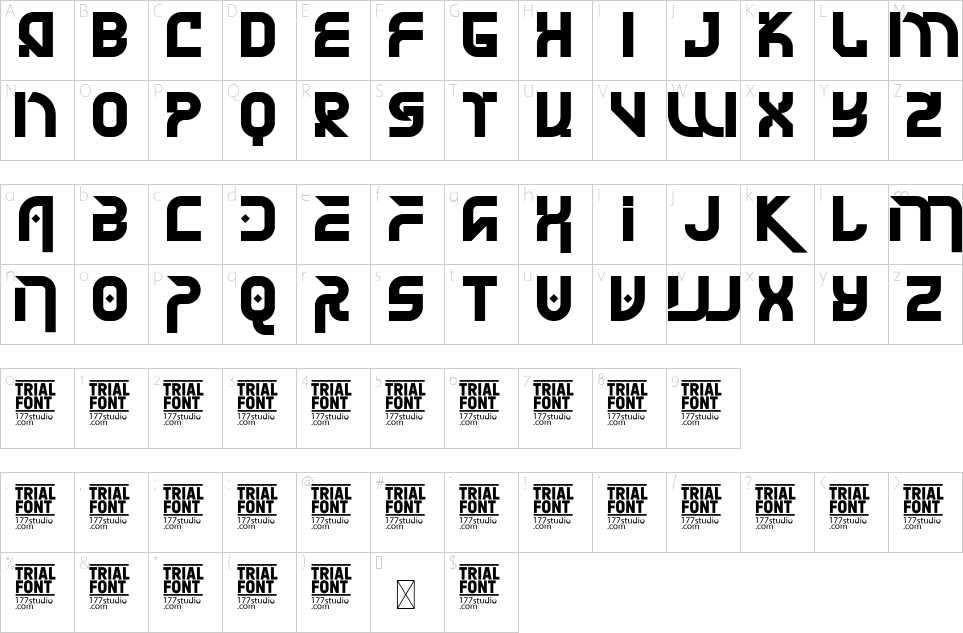
Descubra Process Mastery, uma elegante e profissional fonte gráfica que complementará sua identidade visual. Desenvolvida pelo 177studio.com, Process Mastery foi projetada para ajudar profissionais a organizar e comunicar seus processos de forma clara e eficaz. Esta fonte é uma escolha perfeita para designers, técnicos ou qualquer um que precise de uma fonte que funcione bem tanto em projetos digitais quanto em impressão. Com 1001 fontes gratuitas disponíveis, o catálogo de 177studio.com é um acervo incomparável para qualquer designer. Process Mastery está entre elas, oferecendo uma combinação única de letrasete e legibilidade que é indiscutivelmente útil para manusear processos complexos de forma simplificada. Desenvolvida por uma equipe experiente, esta fonte atende a uma ampla gama de necessidades, tornando-a um investimento valioso para qualquer projeto de design. O design clean e minimalista de Process Mastery torna-o uma opção versátil para diversos ambientes, desde ambientes de trabalho profissional até design de interfaces de usuário intuitivas. Seja para um documento técnico, um mural de projetos ou até mesmo uma apresentação de PowerPoint, esta fonte será uma aliada valiosa. Tornar-se membro da família de fontes de 177studio.com é uma escolha fácil para qualquer designer em busca de uma fonte versátil e de alta qualidade sem precisar gastar uma fortuna. Download Process Mastery agora e dê um salto em sua identidade visual.